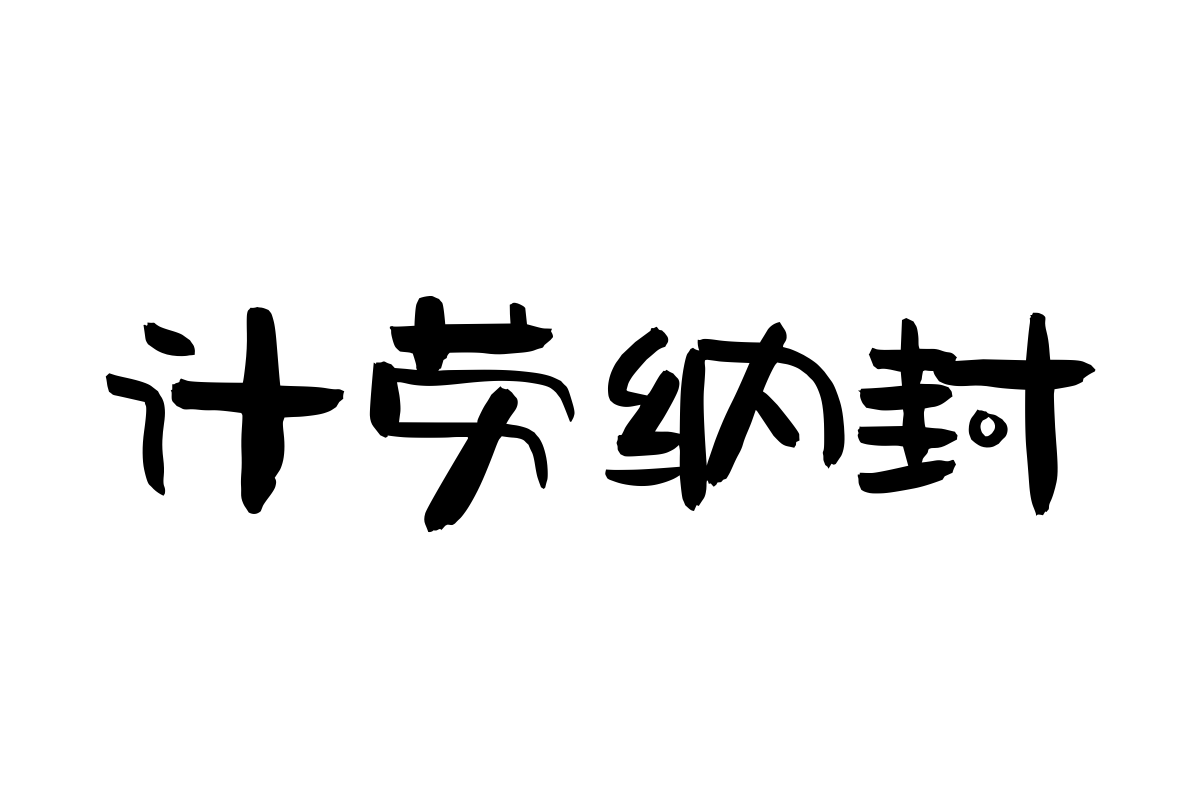
汉仪尚巍砂糖桔字体是一款具有鲜明特点的中文字体。它由汉仪字库设计团队精心打造,旨在为用户提供一种独特而富有个性的视觉体验。
这款字体的最大特点是其独特的砂糖桔形状,这种形状给人一种清新、自然的感觉。同时,砂糖桔的形状也使得字体在视觉上更加醒目,能够吸引人们的注意力。
汉仪尚巍砂糖桔字体的笔画流畅,结构紧凑,既符合汉字书写的基本规则,又具有一定的艺术感。这使得它在各种应用场景中都能够展现出良好的视觉效果,无论是用于标题、正文还是装饰性文字,都能够达到良好的效果。
此外,汉仪尚巍砂糖桔字体还具有较强的可读性,无论是大字体还是小字体,都能够清晰易读。这对于提高文本的可读性和美观性具有重要意义。
总的来说,汉仪尚巍砂糖桔字体是一款非常优秀的中文字体,它以其独特的砂糖桔形状和良好的可读性,为人们提供了一种全新的视觉体验。